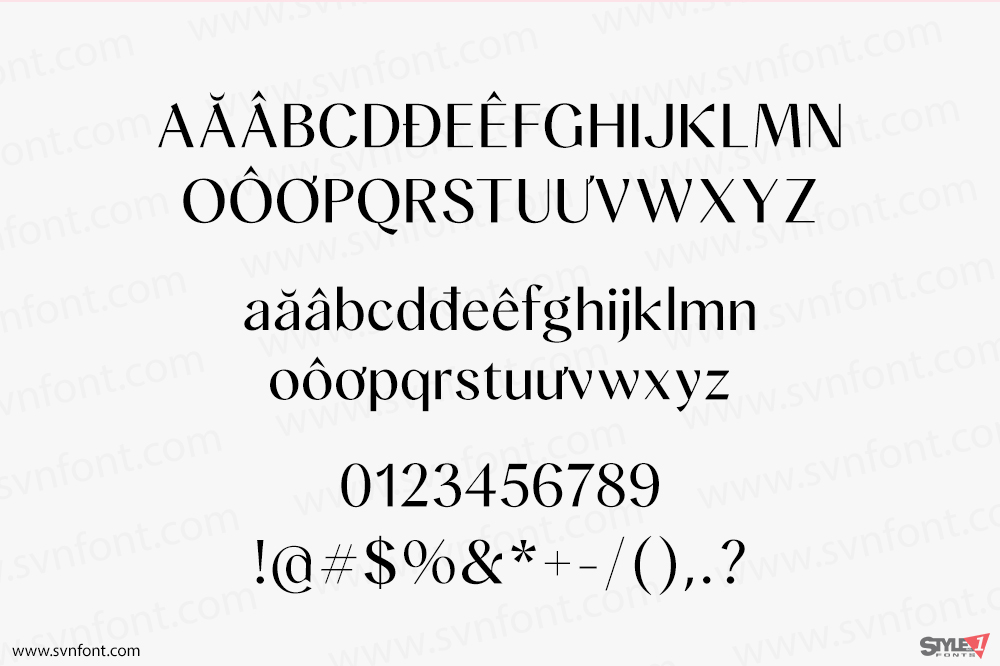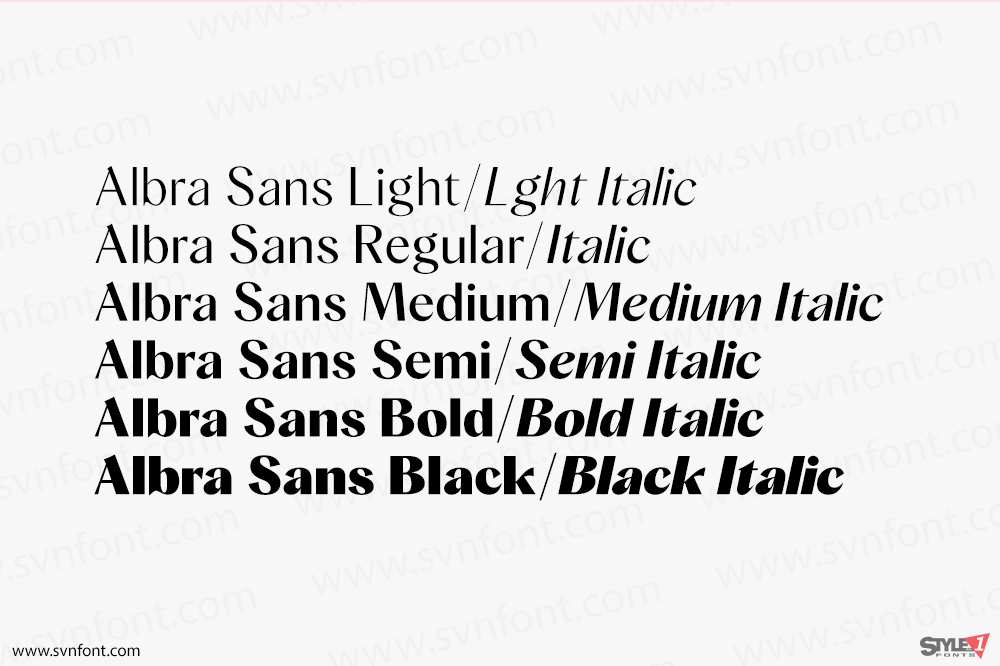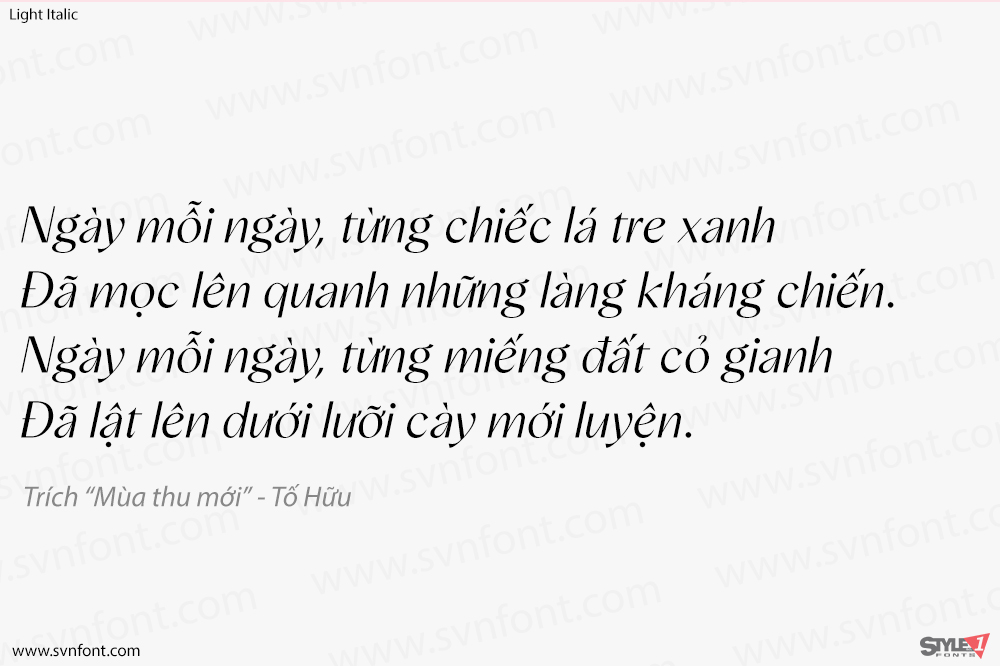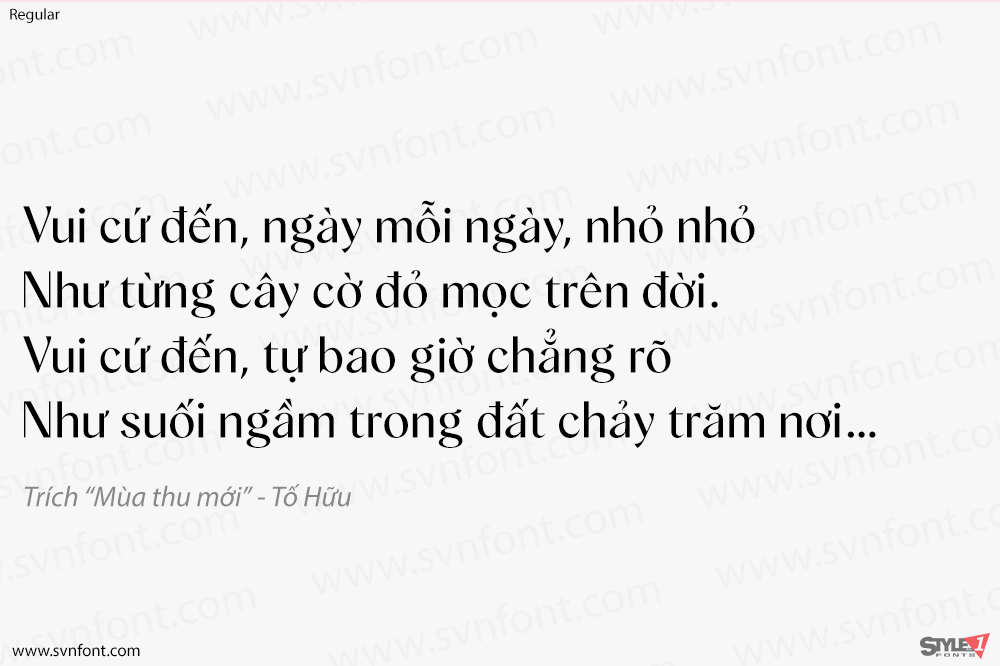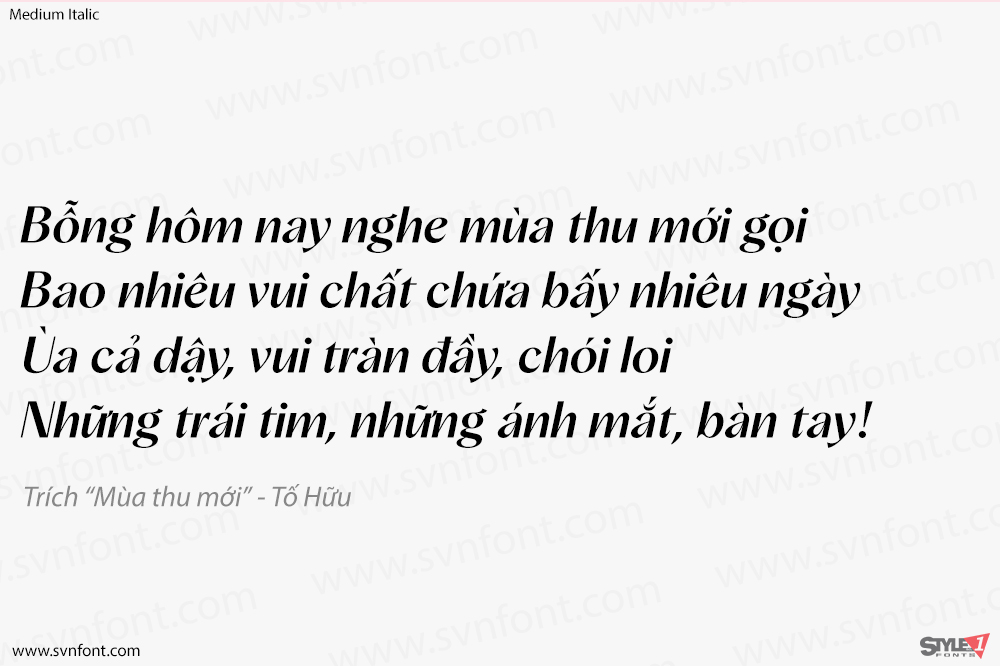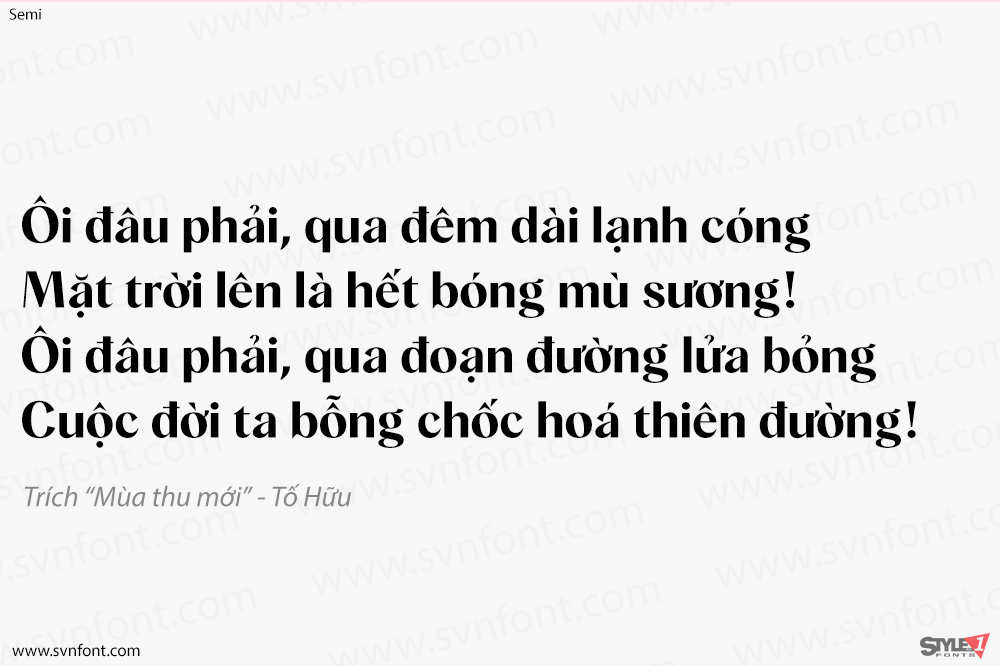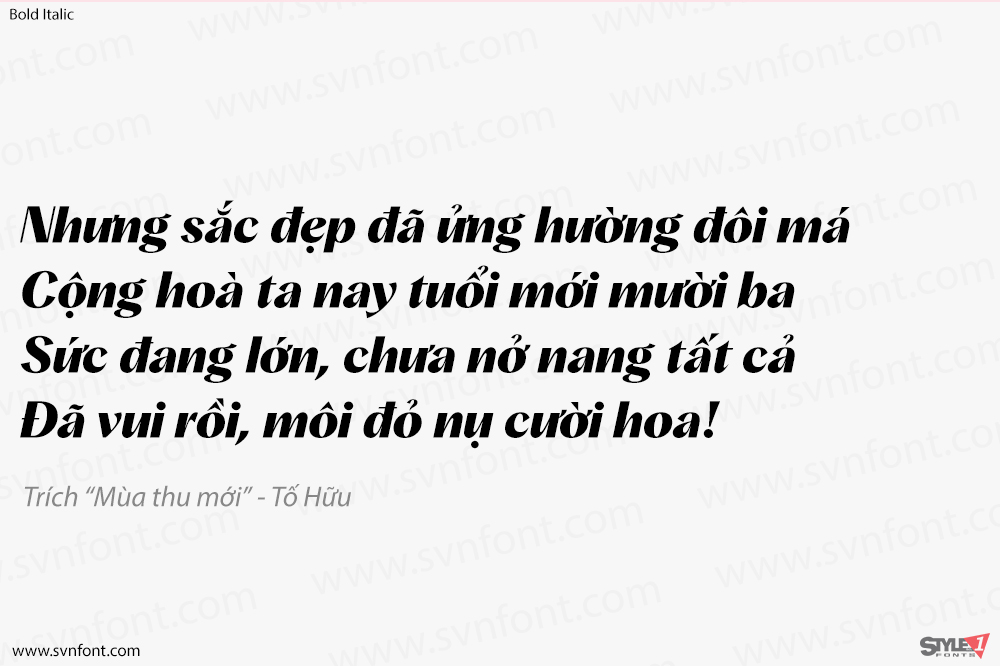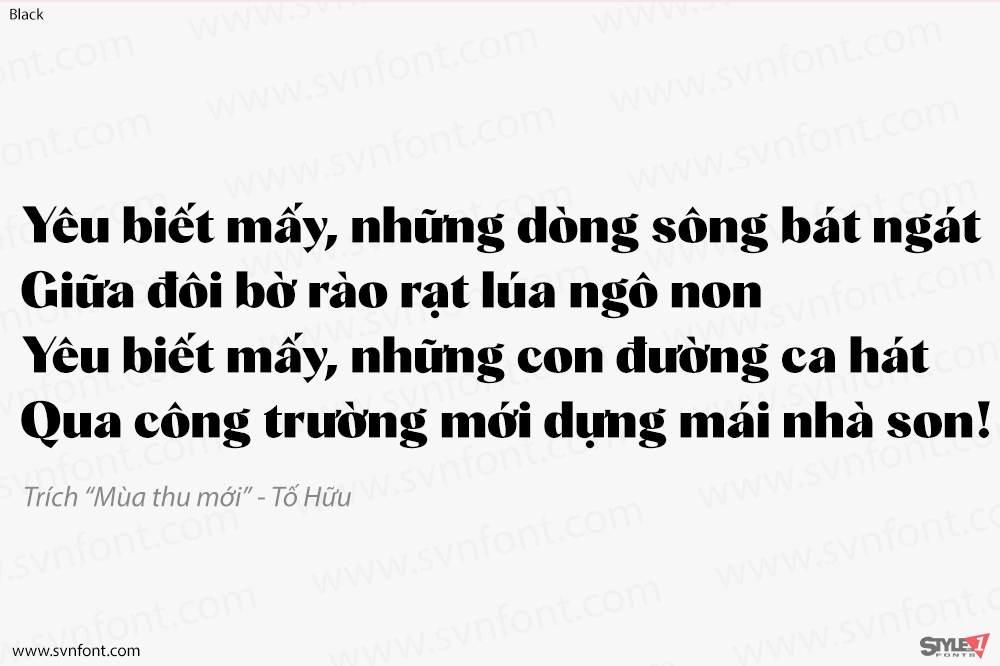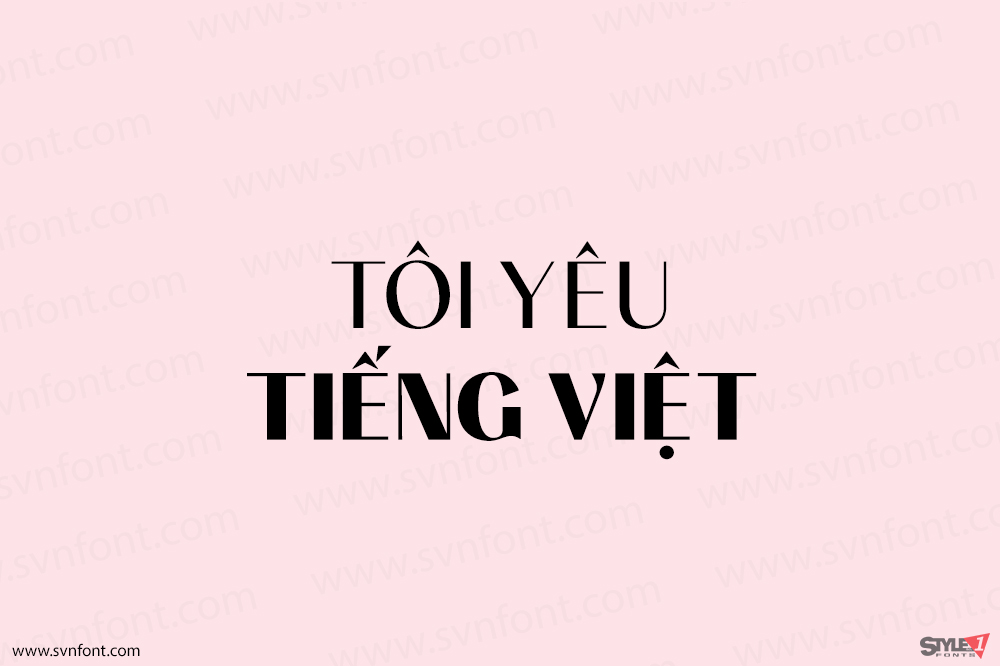
Albra Sans là một sự mở rộng của Bộ sưu tập Albra thành công của chúng tôi. Một kiểu chữ Sans Serif lấy cảm hứng từ thư pháp, vẫn giữ được nét độc đáo ban đầu của bộ sưu tập. Với hơn 500 glyph và nhiều loại độ đậm, nó là một công cụ làm việc bền bỉ, vượt thời gian cho nhiều ứng dụng khác nhau, từ xây dựng thương hiệu đến biên tập.
Nhà thiết kế: Yang Lu
Nhà phát hành: BumbumType